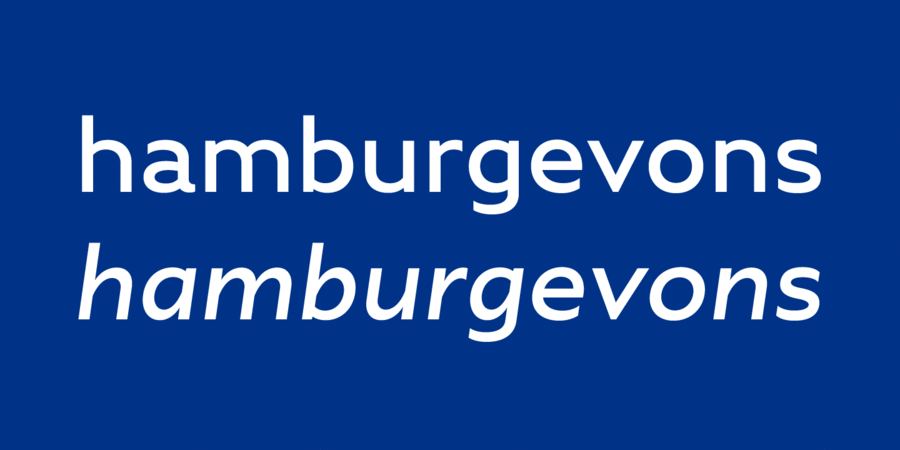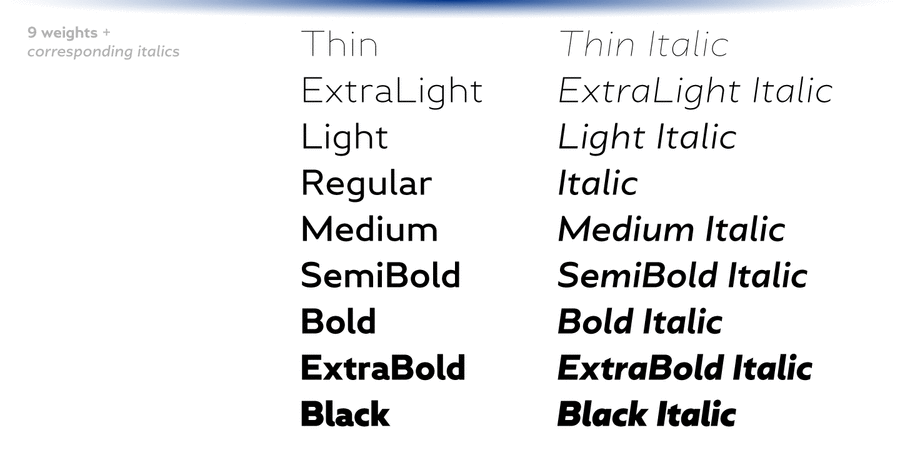
Грінвіч – це сучасний гуманізований ґротеск з відкритою апертурою, натхненний роботами англійських типографів 1910–1920-х років. Гарнітура включає 9 насиченостей з 9-ма відповідними курсивами змішаного стилю. Кожне накреслення містить понад 950 ґліфів. Greenwich пропонує широку мовну підтримку, включно з кирилицею, різні OpenType фічі і безліч альтернативних знаків на вибір. Це сімейство відмінно працює в текстовому складанні, міський навігації, але воно досить виразно для використання в заголовках і в брендінгу. Шрифт розробив і випустив Андрій Константинов в студії Mint Type у 2019 році.
Асоціації з сімейством шрифтів GreenwichОсобистість і характер гарнітури:
мінімалістичний, делікатний, чистий, легкий, прохолодний, свіжий, модний, тонкий, сучасний, лаконічний, рівний, якісний, невагомий, точний, скляний, гострий, прозорий, інтимний, крихкий, дротяний, худий, спокійний, ясний, різкий, чіткий, доступний, комфортний, Простий, глобалізований, глобалістічний, міський, формальний, зрозумілий, розумний, освічений, зручний, серйозний, інженерний, креслярський, діловий, непомітний, твердий, сміливий, мотивуючий, переконливий, яскравий, важкий, сильний, впевнений, стійкий, потужний, помітний, активний, важливий, техногенний, тісний, суворий, амбітний